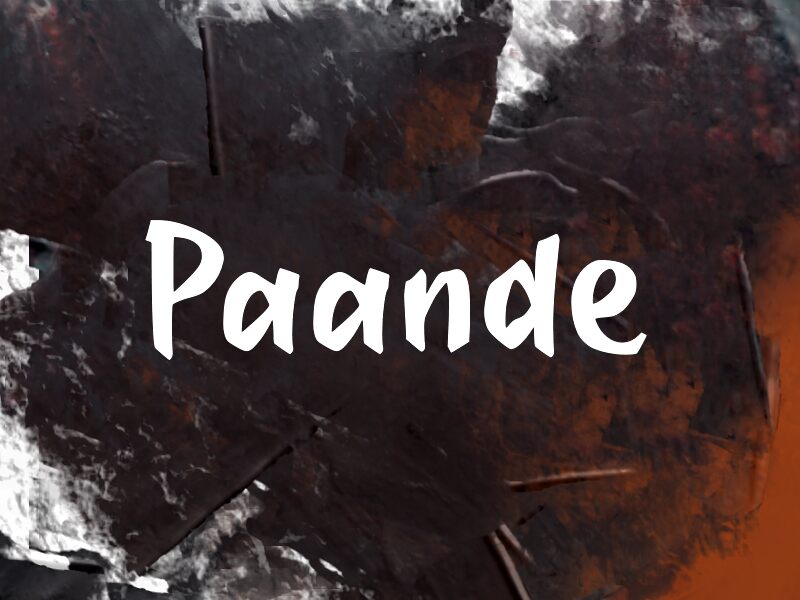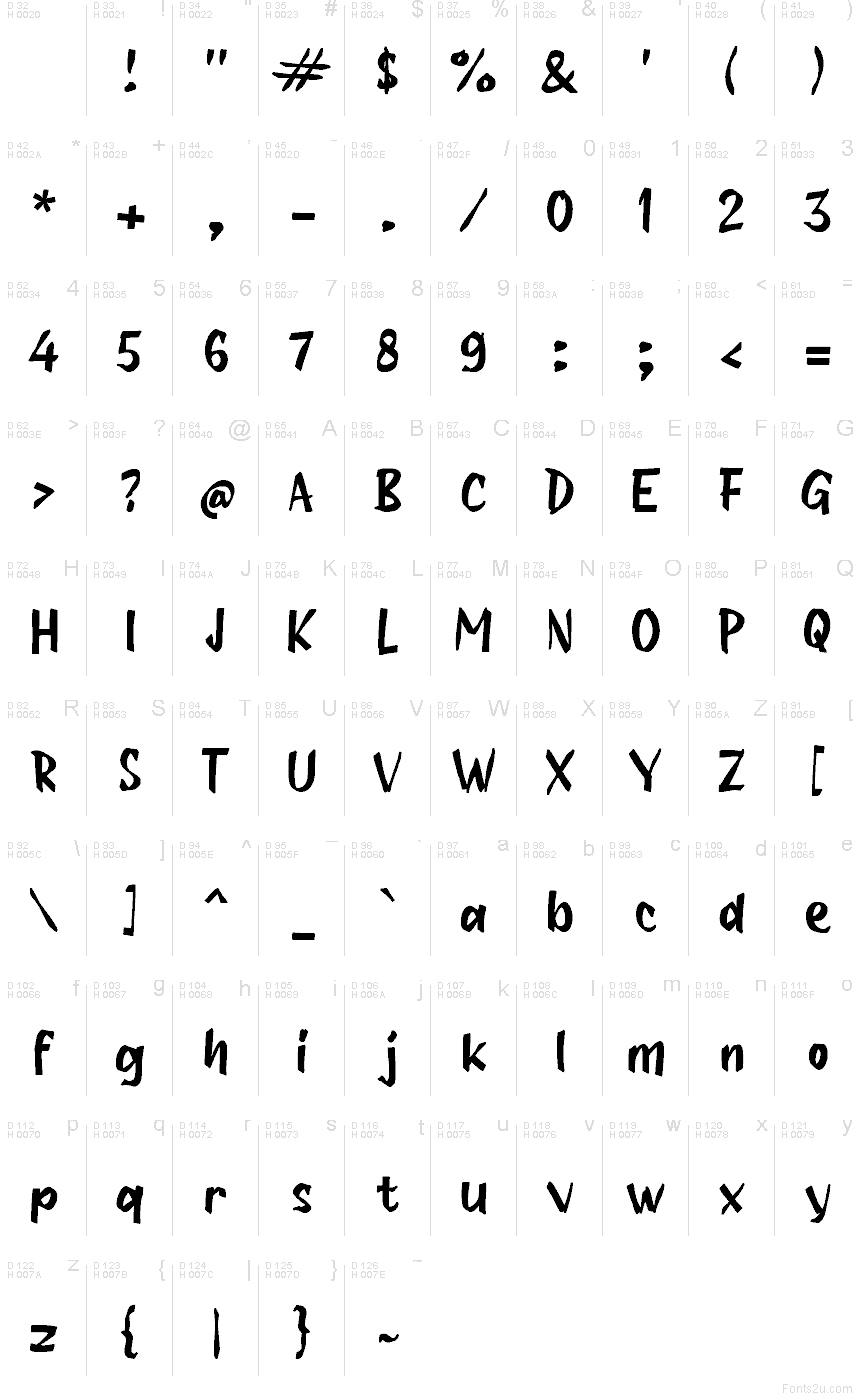
Paande от Wep — это бесплатный кистевой шрифт с дерзким, рисованным от руки характером и легким налетом уличного стиля. Его буквы отличают густые темные мазки, резкие повороты и мягкие неровные края — это придает надписям динамичность, осязаемость и приятную «сырость», лишенную излишней полировки.
Шрифт отлично подойдет для постеров, музыкального оформления, айдентики кофеен, упаковки и графики для соцсетей, где нужен бесплатный шрифт с энергией, но без превращения в чистый граффити-стайл. Используйте его для коротких заголовков или логотипов: компактные формы кисти и срезанные кривые делают даже несколько букв визуально весомыми и «живыми».